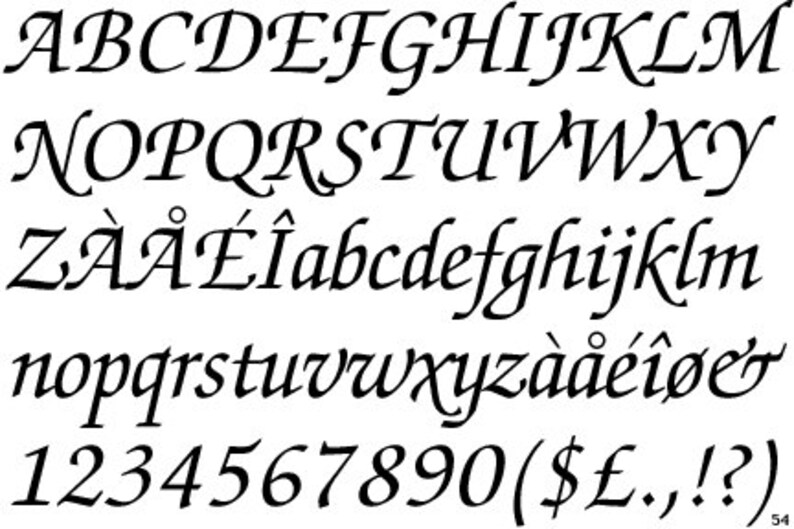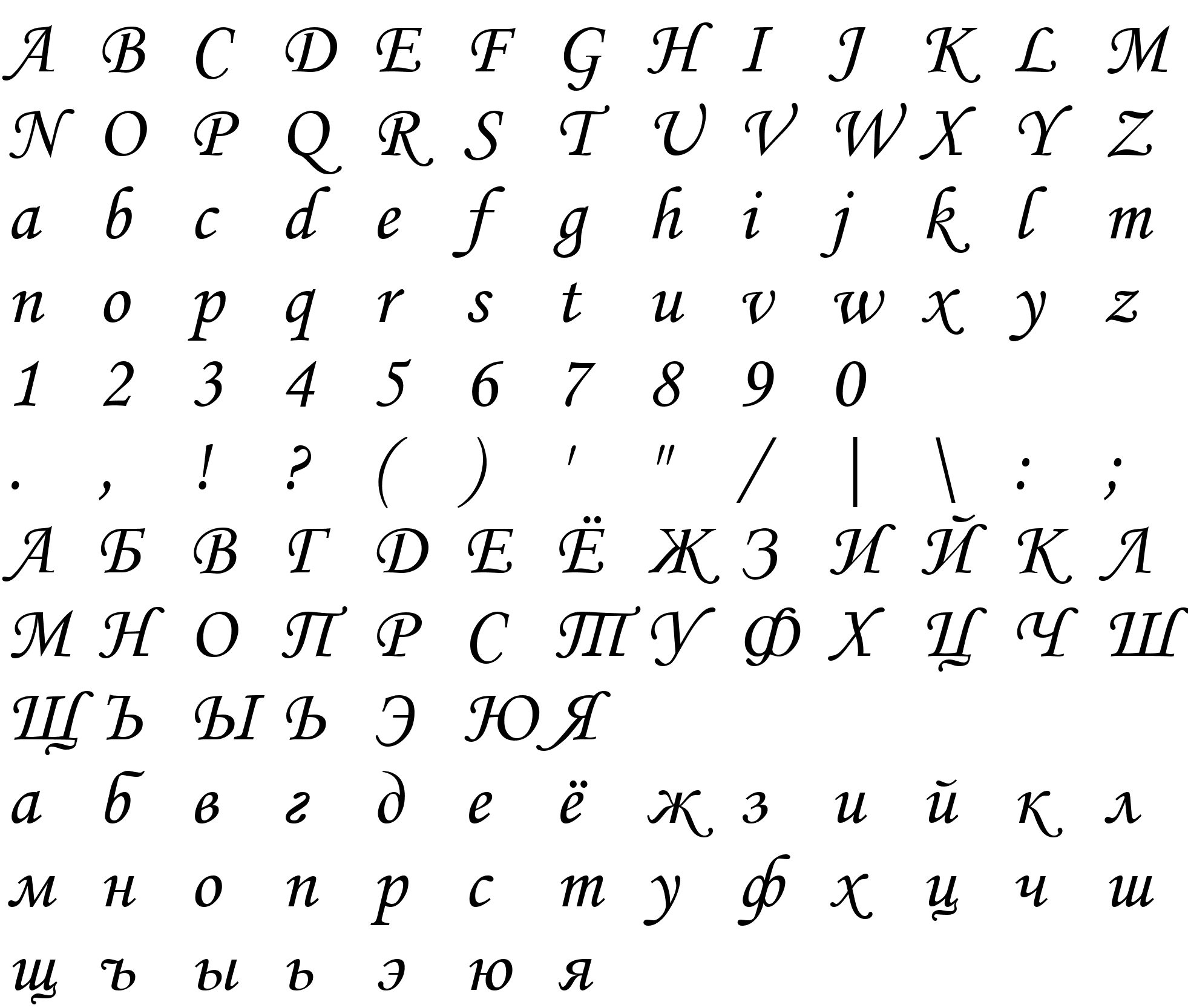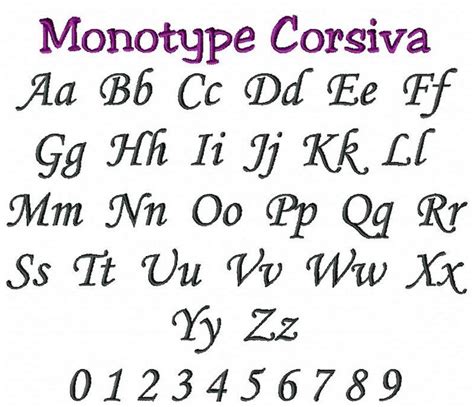
Лучшие советы по применению шрифта Monotype Corsiva в графическом дизайне
Шрифт Monotype Corsiva — это популярный курсивный стиль, который подходит для создания утонченных и элегантных надписей. На этой странице вы найдете полезные советы и рекомендации по использованию этого шрифта в дизайне различных проектов. Изучите, как использовать Monotype Corsiva, чтобы добавить изысканности и читабельности вашим текстам.
Для достижения максимальной читаемости избегайте использования Monotype Corsiva для длинных текстов, так как курсив может затруднять восприятие.
Monotype Corsiva идеально подходит для создания заголовков и элементов брендинга, где нужно подчеркнуть элегантность и стиль.
При использовании шрифта Monotype Corsiva, старайтесь сочетать его с более простыми шрифтами, чтобы сохранить гармонию и сбалансированность дизайна.
Обратите внимание на размер шрифта: Monotype Corsiva выглядит лучше в средних и крупных размерах, где его плавные линии и характерные изгибы хорошо видны.
Используйте Monotype Corsiva в сочетании с минималистичными элементами дизайна, чтобы избежать перегрузки визуального восприятия.
Выбирая Monotype Corsiva для текста, учитывайте его стиль: он лучше всего смотрится в контексте элегантных и торжественных проектов, например, приглашений или свадебных карт.
Не используйте Monotype Corsiva в проекте, где требуется строгая и профессиональная типографика, так как этот шрифт имеет достаточно неформальный и декоративный характер.
Для создания контраста используйте Monotype Corsiva в сочетании с современными шрифтами без засечек, такими как Arial или Helvetica.
Монтипе Корсива не рекомендуется использовать в больших количествах на странице, чтобы не перегрузить восприятие зрителя.
Для печатных материалов и веб-дизайна Monotype Corsiva можно использовать для выделения ключевых фраз или цитат, при этом важно контролировать общую гармонию композиции.